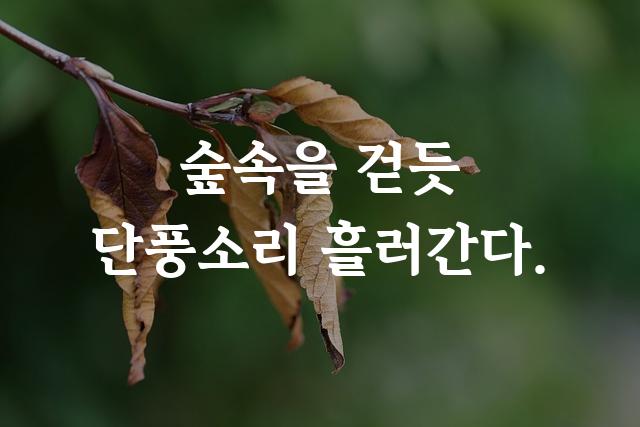
김정철고딕은 기본 고딕 스타일의 문서용 폰트로, 깔끔하고 읽기 쉬운 디자인이 특징입니다. 모던하면서도 실용적인 디자인으로 다양한 문서 작성에 적합합니다.
김정철고딕은(는)
기본 고딕, 감성적인, 부드러움 계열의 생김새를 가지고 있으며
웹/앱 디자인, 프레젠테이션, 보고서/문서 등에서 자주 활용되며, 효과적인 메시지 전달에 적합합니다.
이 폰트는 출판/미디어, 기술/IT, 금융/비즈니스 분야에 잘 어울리며,
명확한, 전문적인, 단순한 느낌을 담고 있는 것이 특징입니다.
이 폰트와 유사한 폰트로는 나눔바른고딕, 고딕A1, 말랑말랑체 등이 있어요. 함께 비교해 보시면 좋습니다!